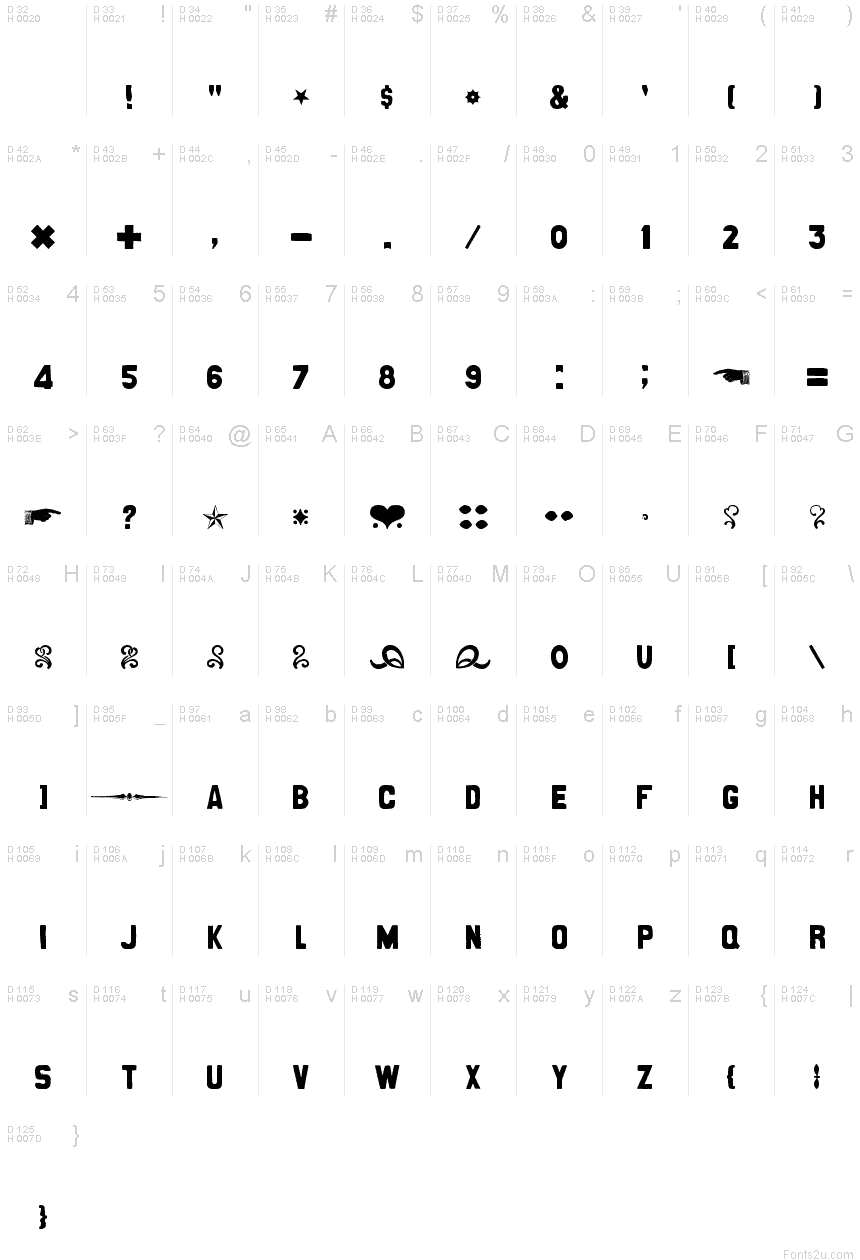
CanCan de Bois to darmowy, ozdobny krój wyświetlaniowy, który zamienia każde słowo w wyrazisty imprezowy szyld. Masywne, czarne jak tusz litery stoją ramię w ramię, urozmaicone zabawnymi kształtami kapsułek i przerośniętym sercem, które wygląda jak wyjęte prosto z karnawałowego baneru. Krój ma wycinaną, niemal szablonową teksturę, która sprawia wrażenie ręcznie wykonanej i lekko surowej, dzięki czemu nagłówki zyskują głośny, przyjazny charakter zamiast wygładzonego szepnięcia.
CanCan de Bois to idealny sposób na przyciągnięcie uwagi w promocjach walentynkowych, zaproszeniach, opakowaniach słodyczy, plakatach, efektownych naklejkach i grafikach do mediów społecznościowych, które mają zatrzymać przewijanie ekranu. Ten darmowy font najlepiej sprawdza się w dużych rozmiarach, gdzie jego serduszka i masywne krzywizny mogą w pełni wybrzmieć; w tekście głównym połącz go z czystym krojem bezszeryfowym, aby radosna energia pozostała tam, gdzie jej miejsce – w Twoich tytułach i krótkich hasłach.
CanCan de Bois
gF Can-Can de Bois
CanCan de Bois
gravemanFOUNDRY 2003
CanCandeBois
Germán Ventriglia|gravemanFOUNDRY 2003